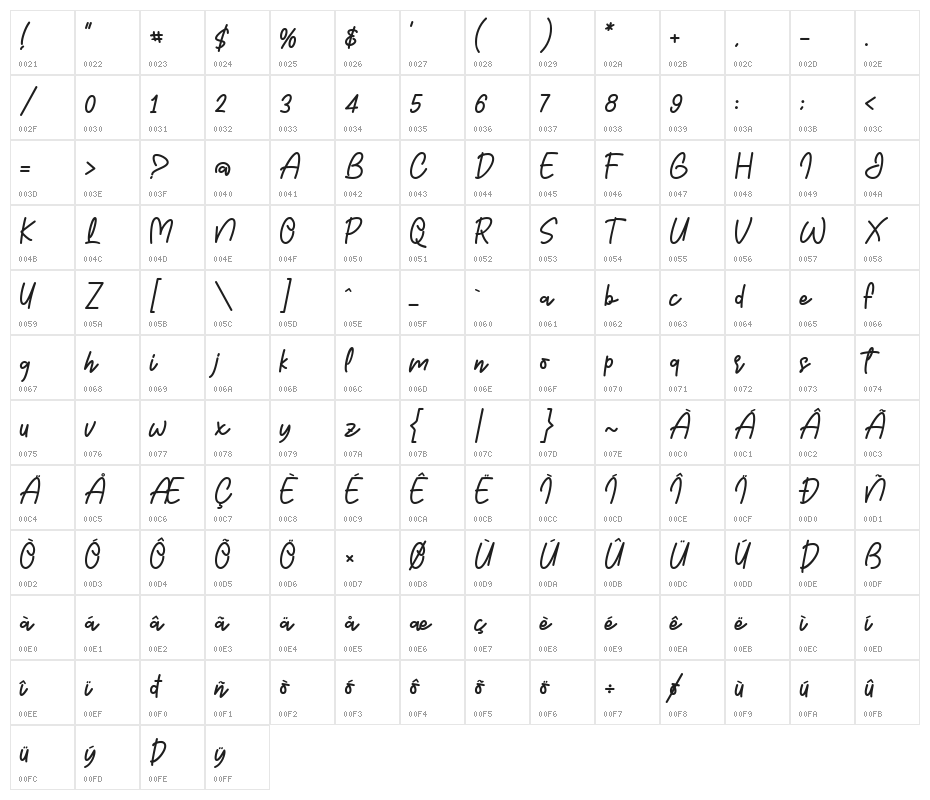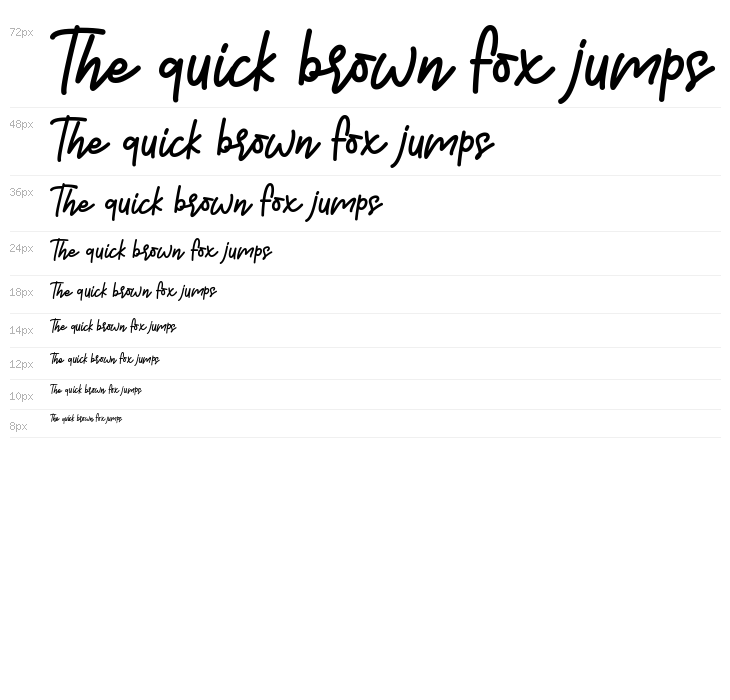
a Good Holiday Font
| Gesamtstil | Casual, Playful, Handwritten |
| Anwendungsfall | Logos, Headlines, Greeting cards, Invitations |
| Vorgeschlagene Projekte | Greeting cards, invitations, social media graphics, branding for creative businesses, informal posters. |